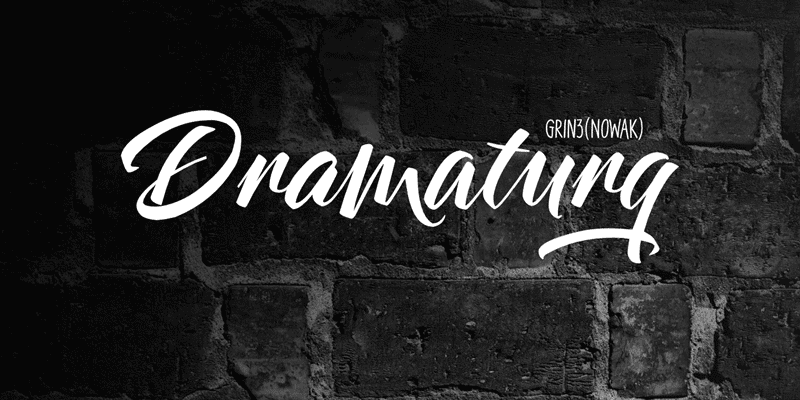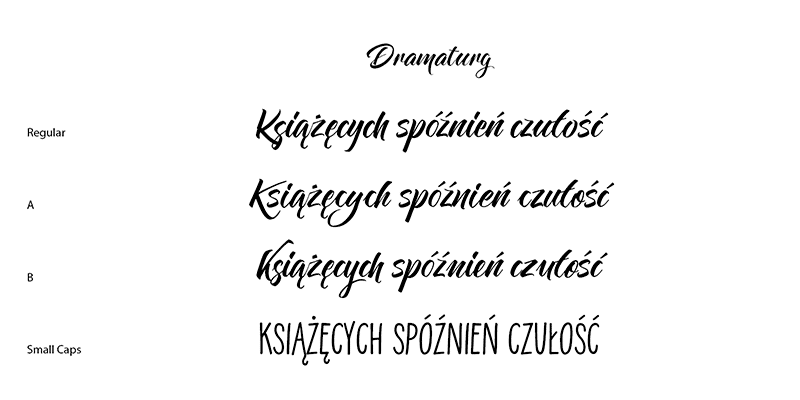
Font Dramaturg
Zakupiliśmy nowy font komputerowy Dramaturg. Został on wykonany przez polskiego projektanta Bartka Nowaka. Rodzina składa się z 4 odmian stylizowanych na pismo ręczne.